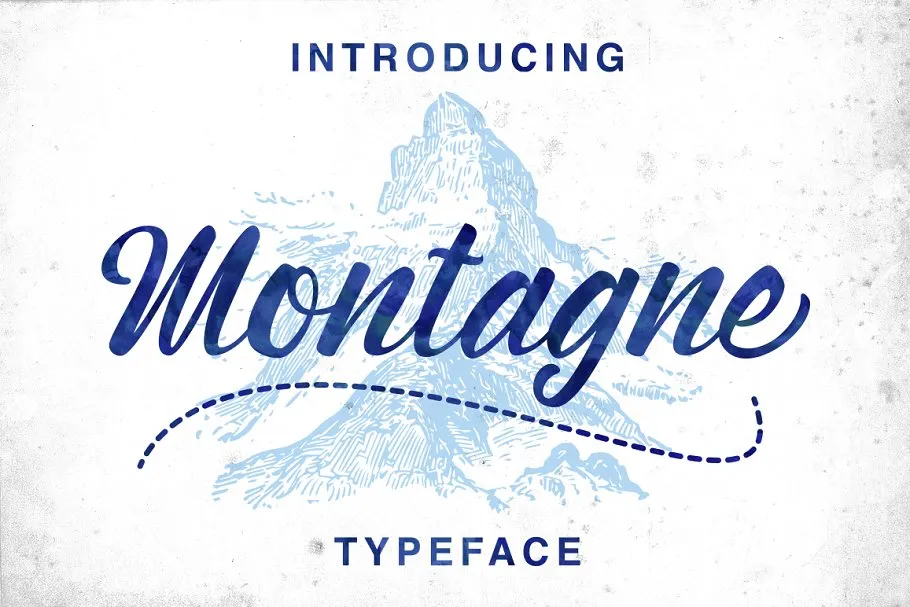
Montagne Script Font – Download Grátis
Introduzimos a Fonte Montagne Typeface . Esta delicada tipografia script é inspirada numa pintura à mão que transmite uma aparência natural. Com alternativas de caracteres contendo ligaturas e outros detalhes, esta fonte é perfeita para diversos fins, incluindo roupas de marca, logotipos impressos, convites e overlayes de imagens, cartões de agradecimento e embalagens de produto, cabeçalhos de texto, design de livros e até mesmo pinturas. Ela é ideal para qualquer projeto que precise de um toque natural e pessoal. Seja para cartões de aniversário ou capas de livro, esta fonte oferece uma variedade incrível que vai atrair e enriquecer seus trabalhos. A Fonte Montagne Typeface da 0001themes é a escolha perfeita para quem procura um toque único e emocional em suas criações visuais.